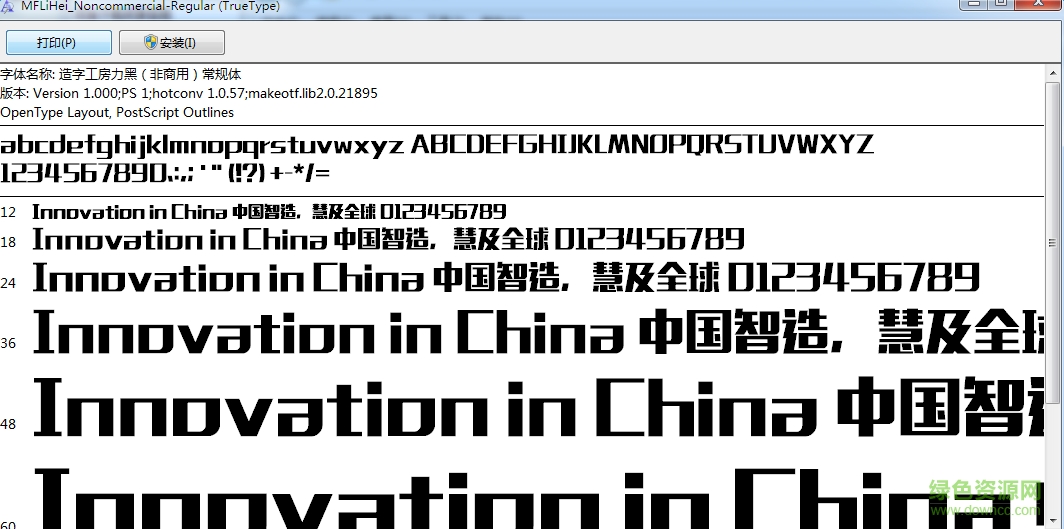
造字工房力黑体常规体是一款极具现代气息的电脑字体,字形非常的优美,整体形态给人以明朗、坚实之感,传达给人果敢和进取的态度。喜欢这款字体的朋友欢迎来绿色资源网下载体验!
造字工房力黑体笔画厚重,强有力度,字形苍劲,笔势顿挫有序,直角与圆角的搭配使字形整体特征刚柔并济,极具现代感。具有较大范围的应用空间。尤其在促销或竞技视觉环境中有良好的表现力!